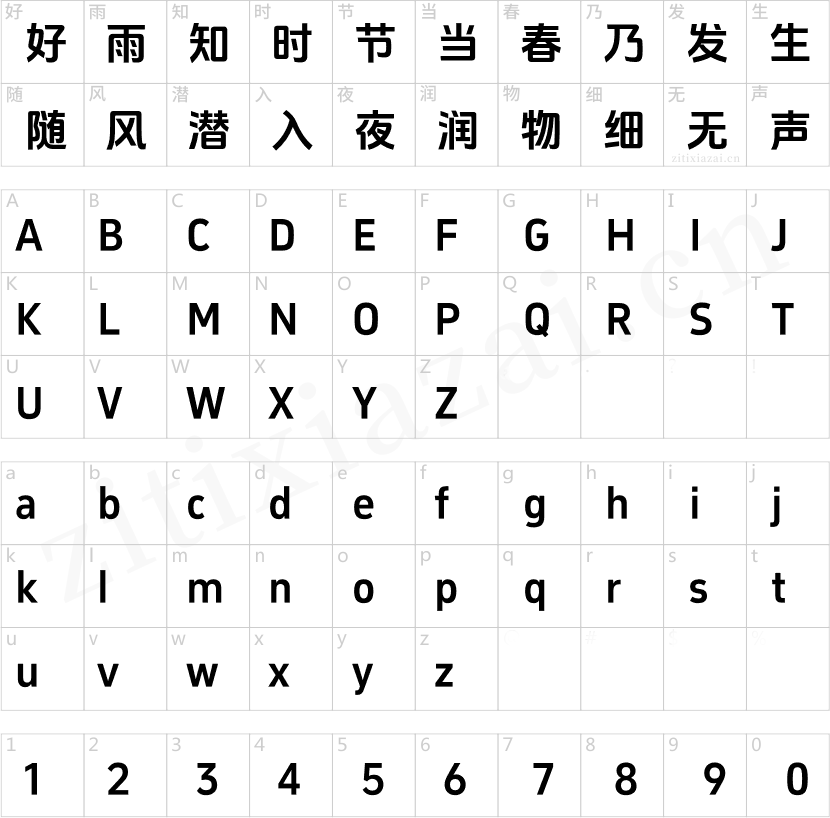
抖音美好体
抖音美好体,这款字体结构工整、笔画清晰,兼顾美观与易读性,适用于标题、正文、海报、包装、LOGO 等多种场景。字形优雅稳定,风格百搭耐看,适配日常排版与创意设计,让文字呈现更舒适、更具质感。抖音美好体一笔一画,皆是细节,以均衡的比例、流畅的线条打造舒适视觉体验,字形端正大气,风格简约现代。无论是商业设计、品牌宣传还是日常排版,都能轻松驾驭,让文字更有格调与力量。抖音美好体字体下载。
字体说明:2023年,抖音已经从短视频平台发展为多体裁内容创作与分享平台,将优质内容带给用户的同时,更鼓励每一个人轻松创作与分享,去发现美好、传递美好。为了更好地传播“记录美好生活”的品牌理念,更好地满足品牌长远发展,打造优质的内容创作与产品体验,抖音体验设计中心与方正字库联合设计开发了一款简洁大方、清晰易读,同时兼具现代气质与人文属性的品牌定制字体——抖音美好体。抖音美好体包含6763个中文字符,682个西文及数字符号,执行国家GB2312-80简体中文编码字符标准。作为品牌标准字体,抖音美好体将会率先用于抖音及其子品牌中,助力品牌视觉形象的统一,提升品牌的官方性、权威感。抖音美好体提取了“抖音”logo字体简约清新的风格特征,为适应标题场景的使用,被打造为笔画较粗的大字重字体;90%的大字面率,呈现出美观大方、清晰易读的视觉风格;大中宫设计,使得字体更加舒展饱满,字体具有极强的识别特征。为构建品牌字体的独特性,抖音美好体的笔画细节采用了非常规的圆弧设计和倒角设计。弯勾笔画采用大曲率圆弧曲线,均匀顺滑的线条设计使得字体更流畅优美,更具视觉韧性。折笔笔画则在平衡字体易读性和识别度的基础上,采用了内直外弧的倒角方式,传递出一种“刚柔并济”的人文气息。